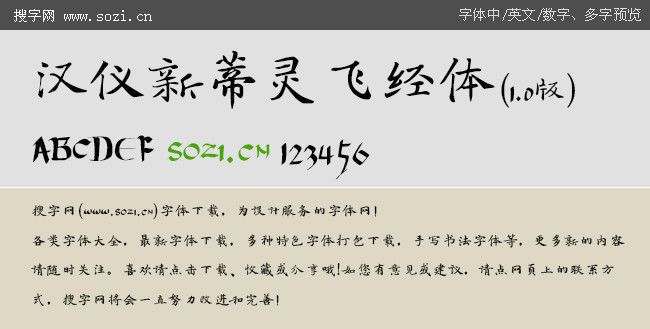
漢儀新蒂靈飛經(jīng)體1.0
搜字網(wǎng)提供一款漢儀新蒂靈飛經(jīng)體1.0字體下載,漢儀新蒂靈飛經(jīng)體是一款漂亮的古風手寫字體。由漢儀新蒂工作室出品,漢儀新蒂工作室成立于2016年,由漢儀字庫與新蒂字體聯(lián)合成立,本字體字跡娟秀得體,更顯飄動靈敏之氣,適合應用于海報設計、書籍設計、藝術(shù)設計、包裝設計等應用。(本字體為個人非商用版,如需要商用請聯(lián)系漢儀公司購買版權(quán))